Tải miễn phí 20 font chữ Retro thanh lịch cho website (P.2)
Trong phần trước, chúng ta đã đến với những mẫu chữ mang phong cách retro đầy cuốn hút.
Bây giờ hãy cùng trở lại với phần tiếp theo của bộ sưu tập này và chọn cho web của bạn một mẫu chữ ưng ý.
CODEX
CODEX có hơn 230 ký tự, đầy đủ bảng chữ cái, bảng số, các ký tự Latin và dấu.
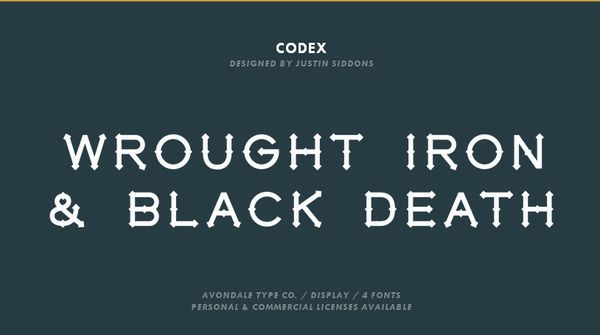
FERAL Free Typeface
Mẫu chữ hơi có phần rung rợn này được dùng ở vị trí heading. Bạn có thể dùng nó cho thiet ke website quảng bá phim kinh dị hoặc website chủ đề Halloween.
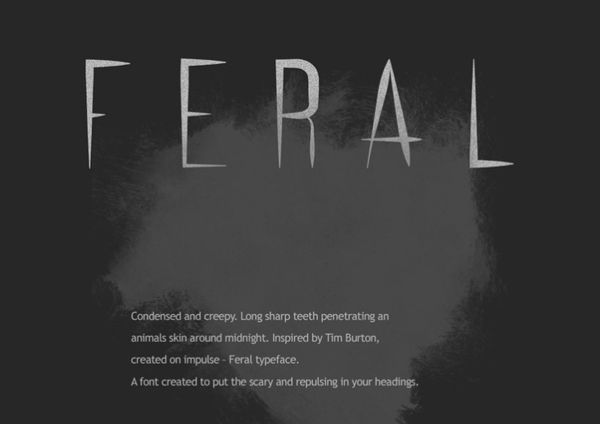
Nautilus Pompilius Font
Nautilus có sự tương phản hợp lý và phong cách hiện đại. Bạn có thể dụng mẫu chữu này cho logo, heading, poster và những vị trí dễ chú ý khác.
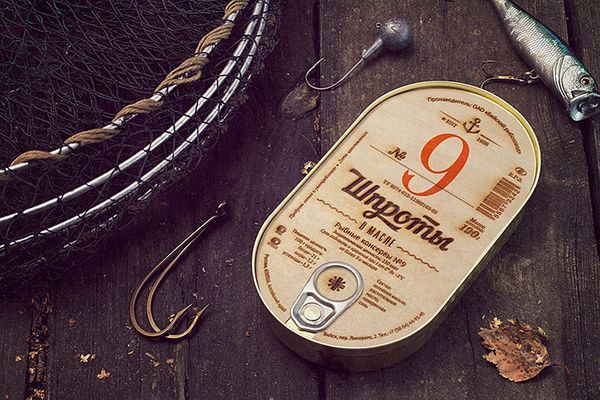
Glamor - Chic & Modern Free Type Family
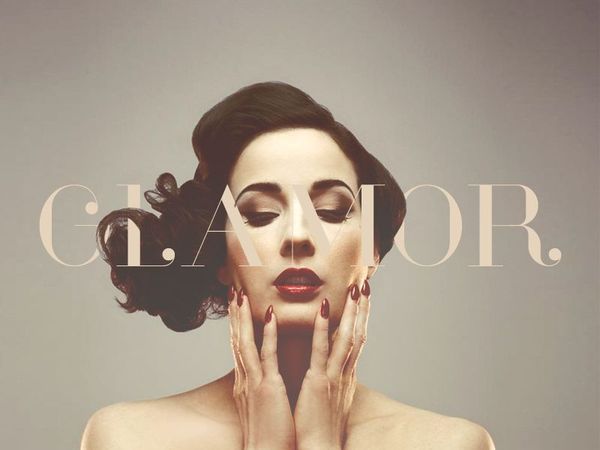
Hagin Free Font
Hagin là font chữ serif miễn phí mới ra mắt . Nó sẽ mang lại cảm giác về thời xưa cũ cho những thiết kế website, áo thun, hoặc các thiết kế đồ họa của thế kỷ hiện đại này.
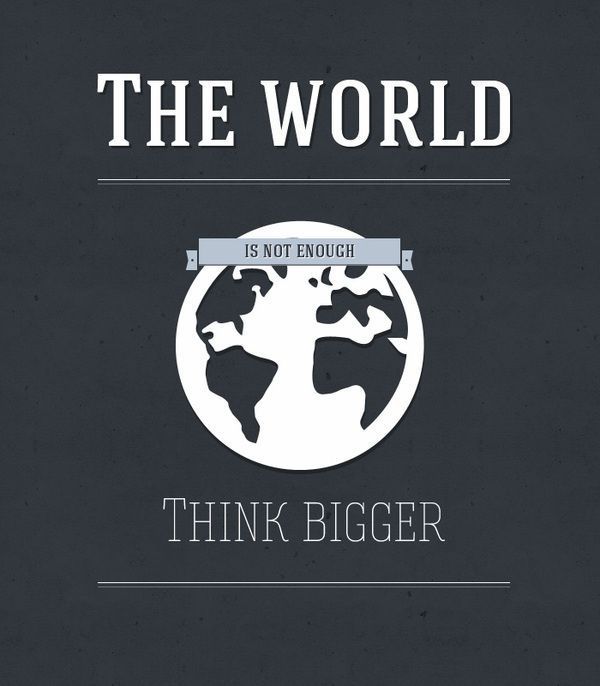
Kraftstoff Typeface
Kraftstoff mà mẫu chữ độc đáo lấy cảm hứng từ is a typeface based on máy bơm khí cổ . Bạn có thể tải miễn phí nó cho thiet ke website của mình.
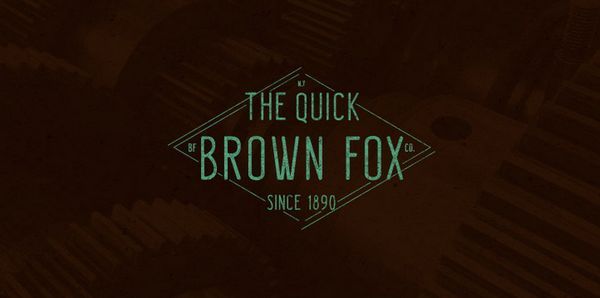
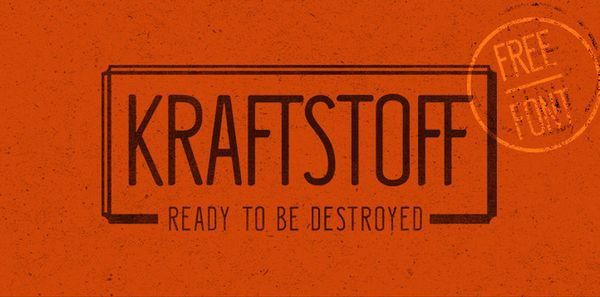
Lichtspiele
Lichtspiele mang bạn trở về vời thời gian khi mà đèn neon và các chữ marquee được dùng để trang trí mặt tiền rạp chiếu phim thời đấy.
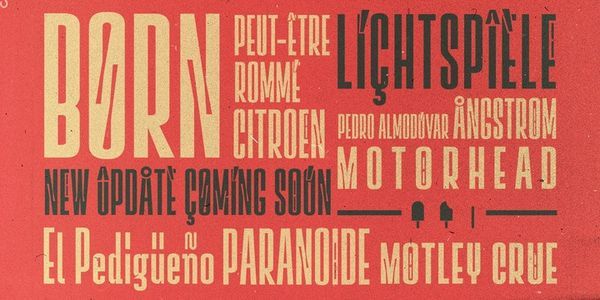
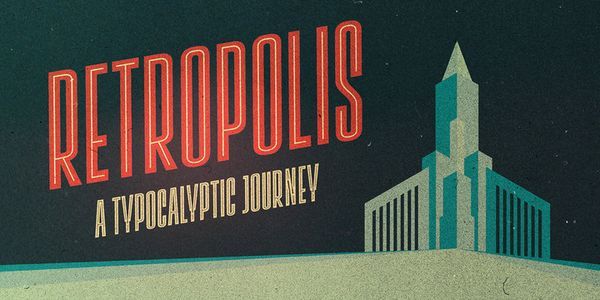
Mohave Typefaces
Mohave rất dễ dàng điều chỉnh kích cỡ. Mẫu chữ được thiết kế cho các vị trí cần typography cỡ lớn ở tiêu đề, headline, poster…Có sẵn các chữ kiểu in hoa và in thường tại file download.
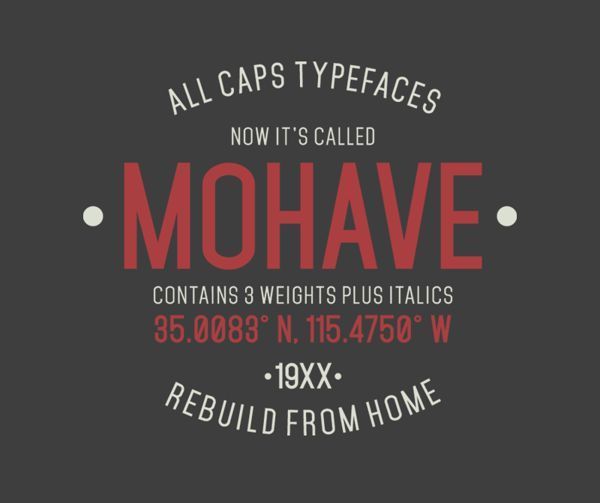
Streetwear (Free Font)
Streetwear là một mẫu chữ đậm đà và cá tính theo phong cách retro. Nó phù hợp để làm logo, poster, nhãn hiệu, bao bì và thiết kế áo thun. Bạn sẽ thấy phong cách thời trang của thập niên 60, 70 tràn về trong các thiết kế sử dụng font chữ này. Bạn có thể chỉnh sửa file downlaode của mẫu chữ này bằng phần mềm Adobe Illustrator và InDesign.